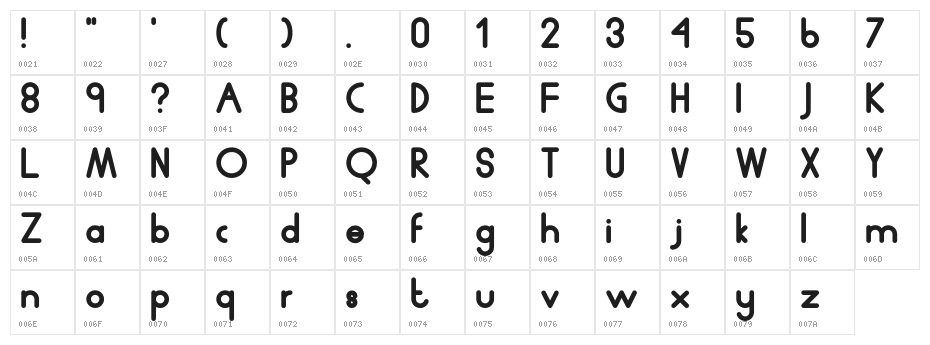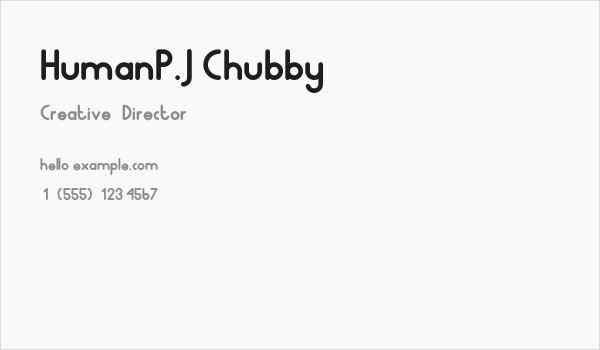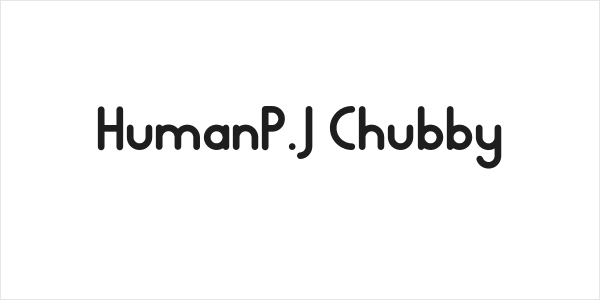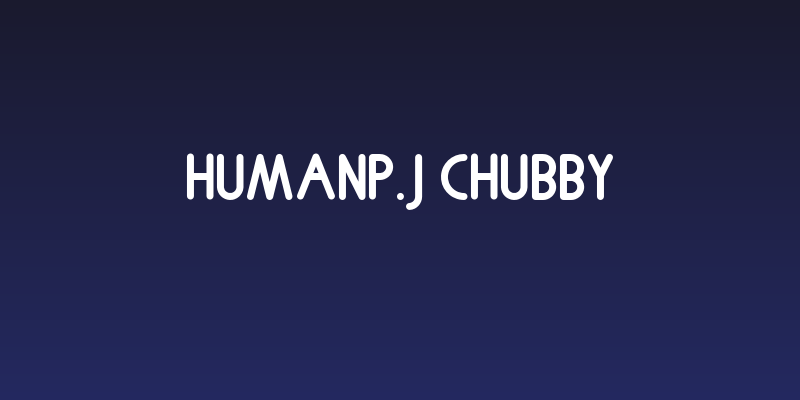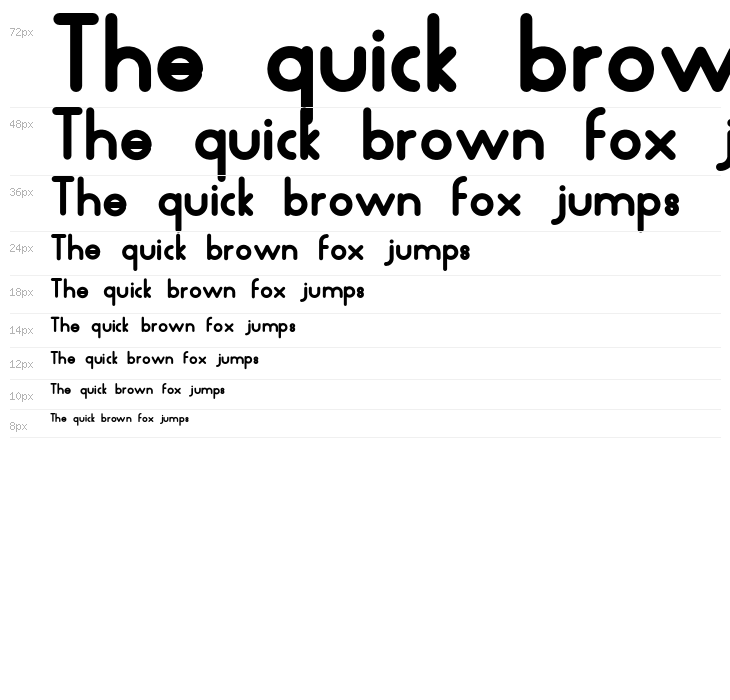
HumanP.J-Chubby Font
| Gesamtstil | Playful |
| Vorgeschlagene Projekte | Ideal for children's books, playful branding, casual invitations, and social media graphics. |